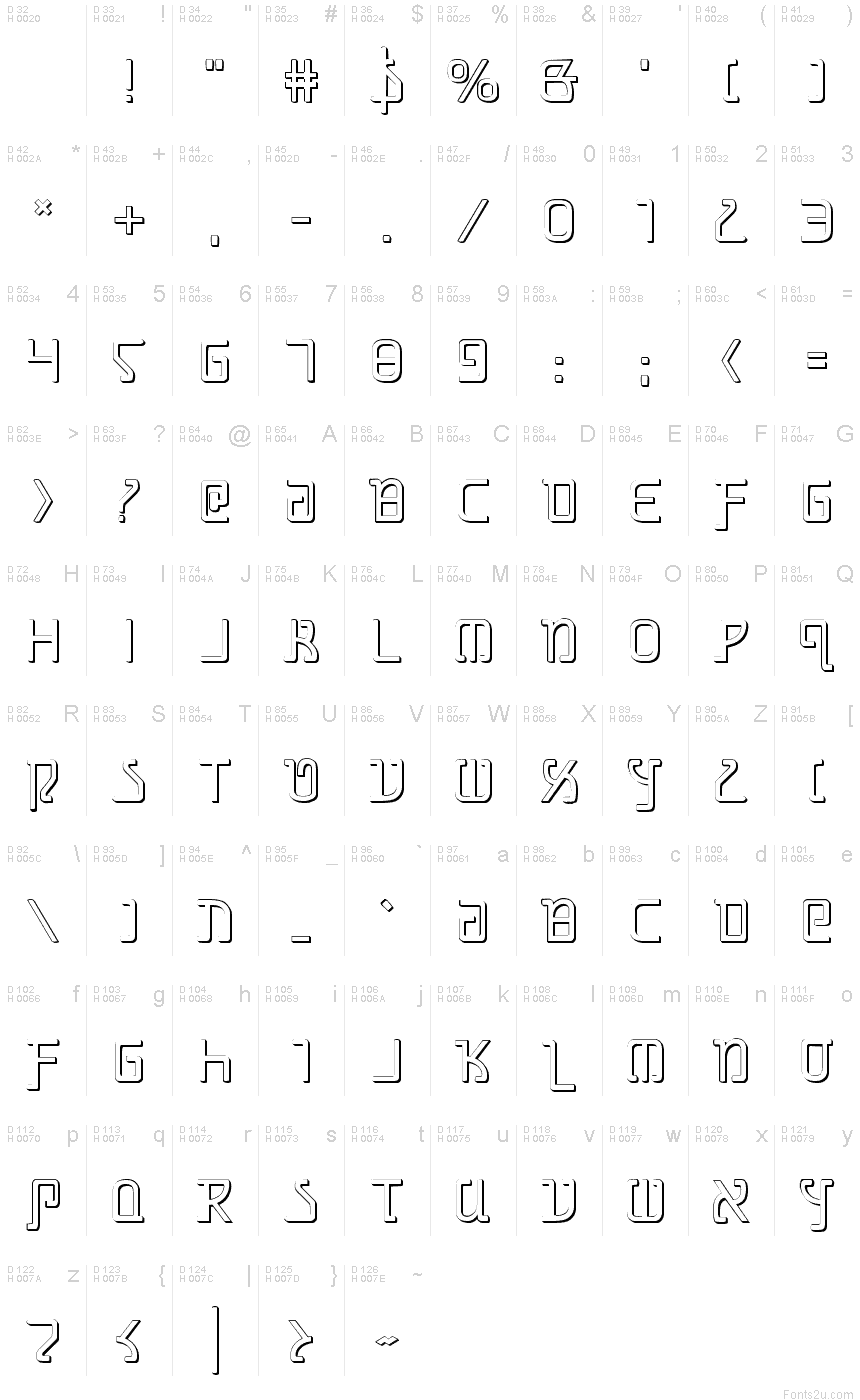
Grimlord Shadow od Iconian Fonts to darmowy, konturowany krój displayowy o twardej geometrii retro napisów science-fiction. Jego wysokie, kwadratowe formy wykorzystują zaokrąglone zewnętrzne narożniki, otwarte linie wewnętrzne i sporadyczne ostre przekątne, dając litery, które wyglądają raczej na zaprojektowane inżynieryjnie niż narysowane ręcznie.
Tytuł gry to jego najbardziej przekonująca rola, szczególnie w przypadku futurystycznych przygód, grafik arkadowych i plakatów science-fiction. Powtarzające się przerwy wewnątrz liter i zakręty przypominające obwody pasują również do opakowań płyt, gdzie motyw mechaniczny może powiązać litery z muzyką elektroniczną i techniczną ikonografią.
Grimlord Shadow